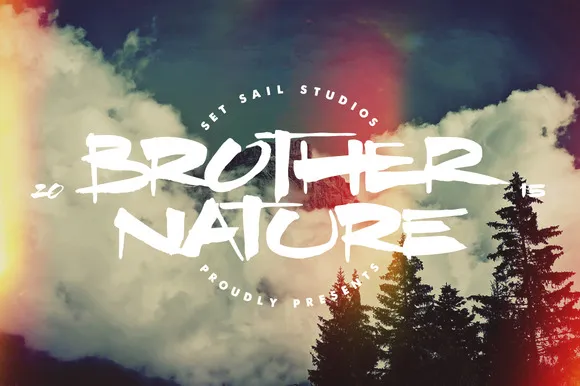
Aqui está uma breve descrição em português para a página de download da font ‘Brother Nature’, ideal para sua categoria de Brush Fonts: Prepare-se para as férias! Idealizado pelo designer Hamilton, Brother Nature é um belo e estiloso traço feito com pincel. Perfeito para textos capazes de chamar atenção em cabeçalhos, publicidade, designs para roupas e até logotipos. Uma fonte leve e elegante que fará seu design brilhar. É uma escolha perfeita para quem busca um traço despojado e divertido para seus projetos. Suave mas com certa rusticidade, Brother Nature será sua aliada em diversos tipos de criações gráficas. Não importa se está trabalhando em camisetas desenhadas ou criando uma marca inovadora – esse pincel é o seu companheiro perfeito para qualquer projeto.